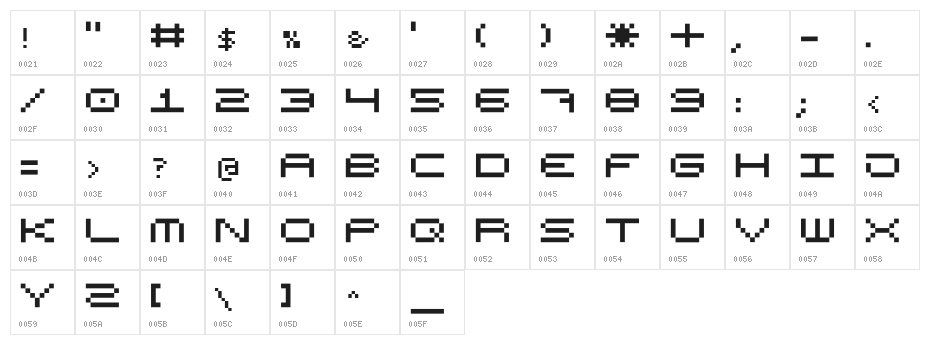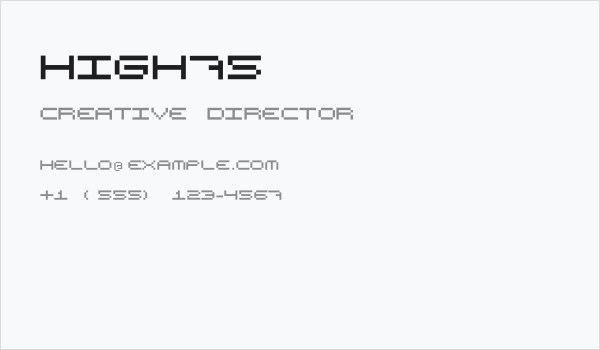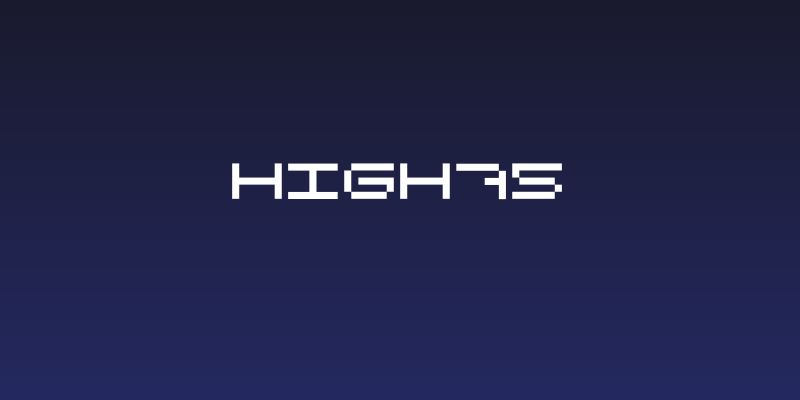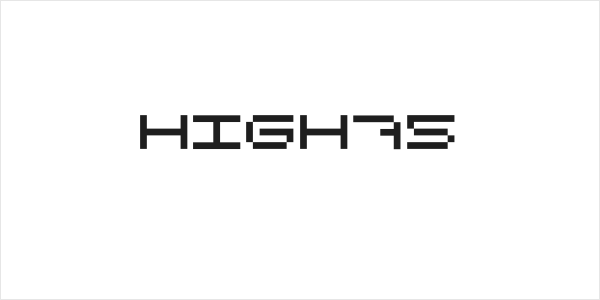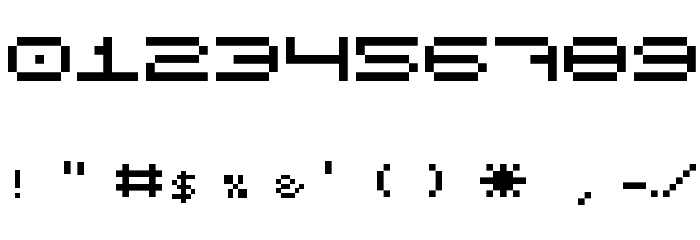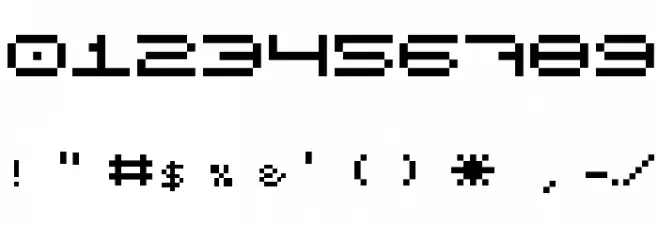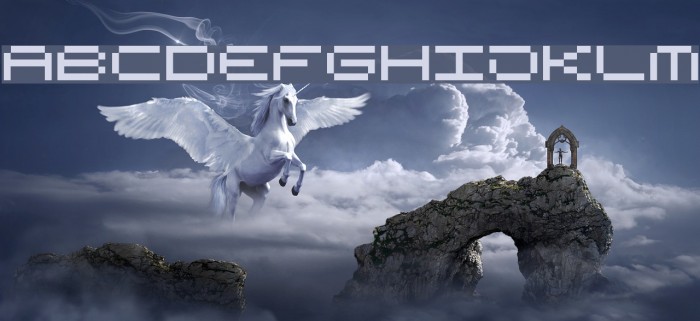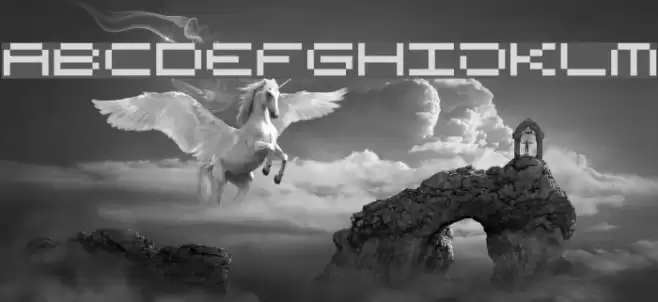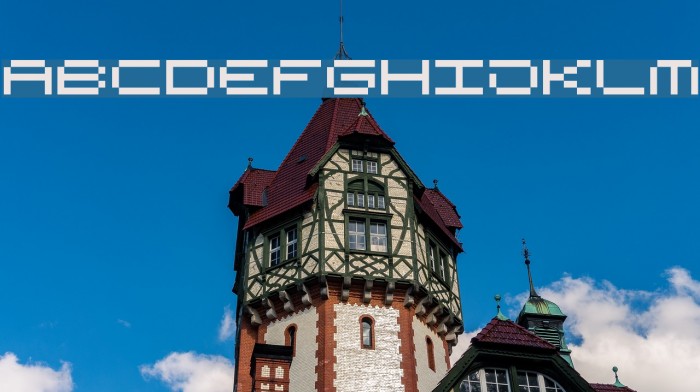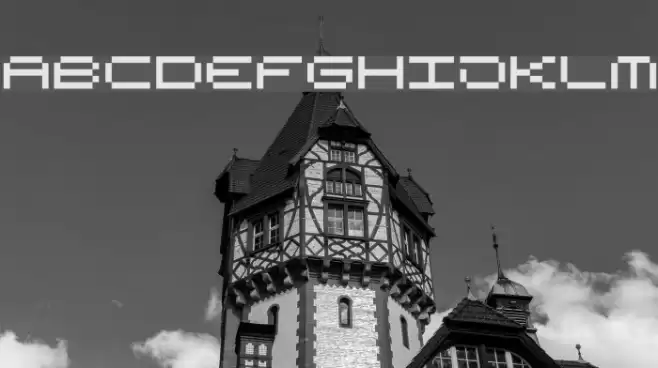
High75 Font
✎ Pixel
| Style général | Retro |
| Cas d'utilisation | Headlines, Logos, Digital displays |
| Projets proposés | Ideal for video game design, digital art projects, retro-themed branding, and tech-related presentations. |